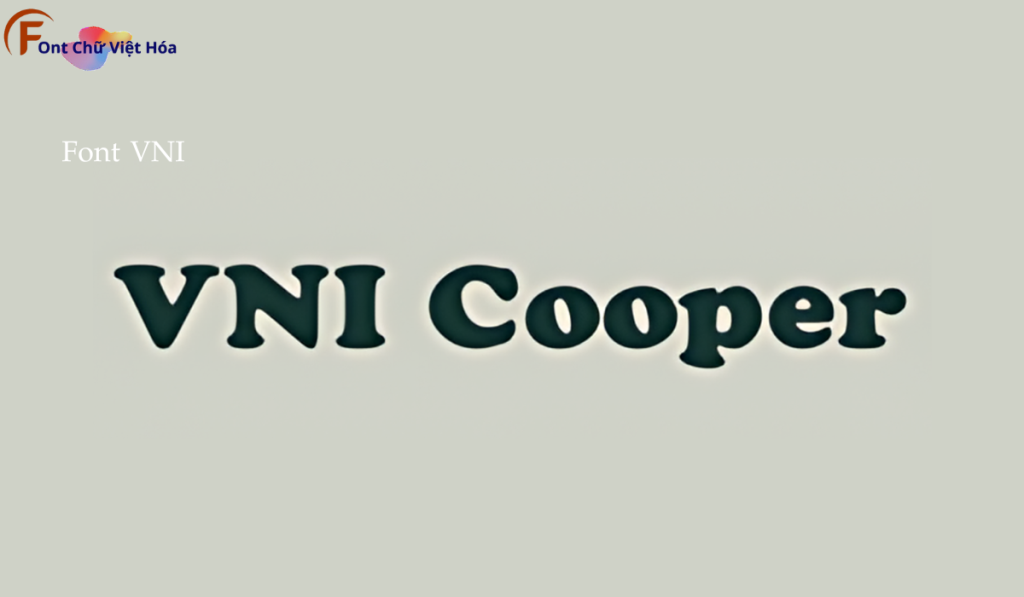
Font VNI Cooper Việt Hóa
Kiểu chữ: Có chân
Font VNI Cooper Việt Hóa, thuộc bộ font VNI, mang phong cách hiện đại và cá tính, lý tưởng cho các dự án thiết kế như poster, logo, và bao bì sản phẩm. Với các nét chữ có chân và độ dày đều đặn, Font VNI Cooper Việt Hóa không chỉ dễ đọc mà còn tạo cảm giác sáng tạo và độc đáo. Việc Việt hóa font giúp người dùng dễ dàng tích hợp vào các thiết kế tiếng Việt, mang lại sự tiện lợi và nâng cao tính thẩm mỹ.